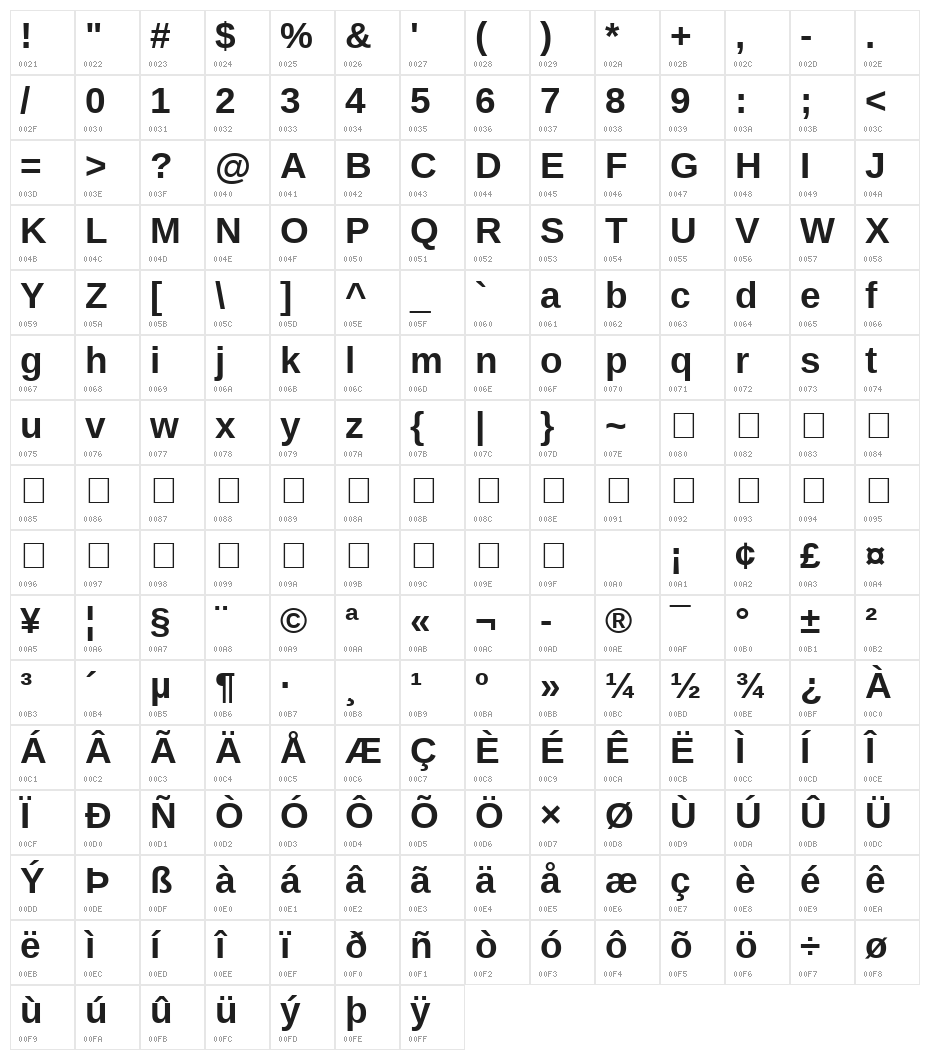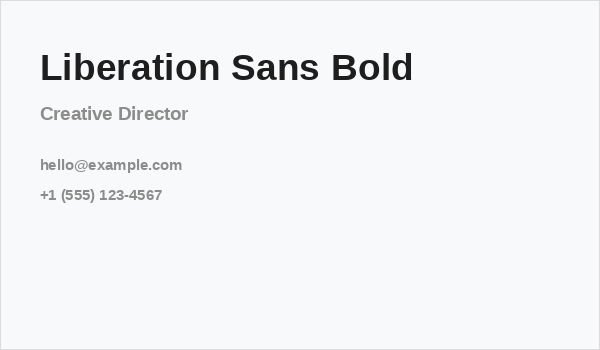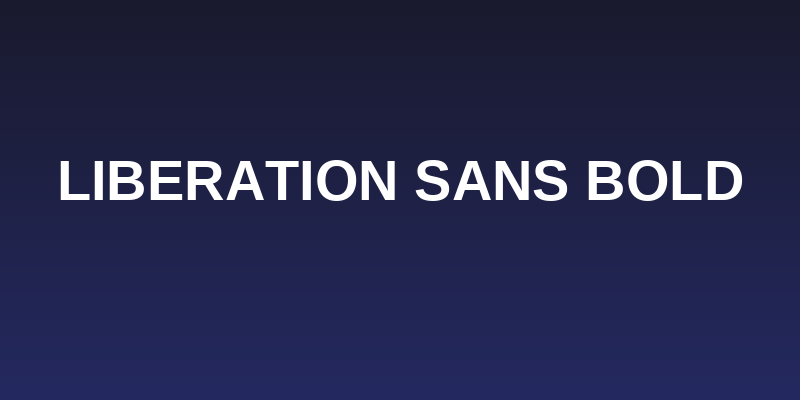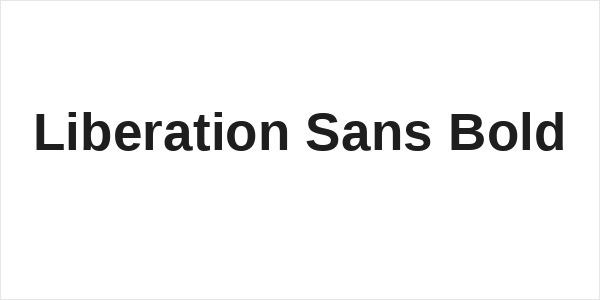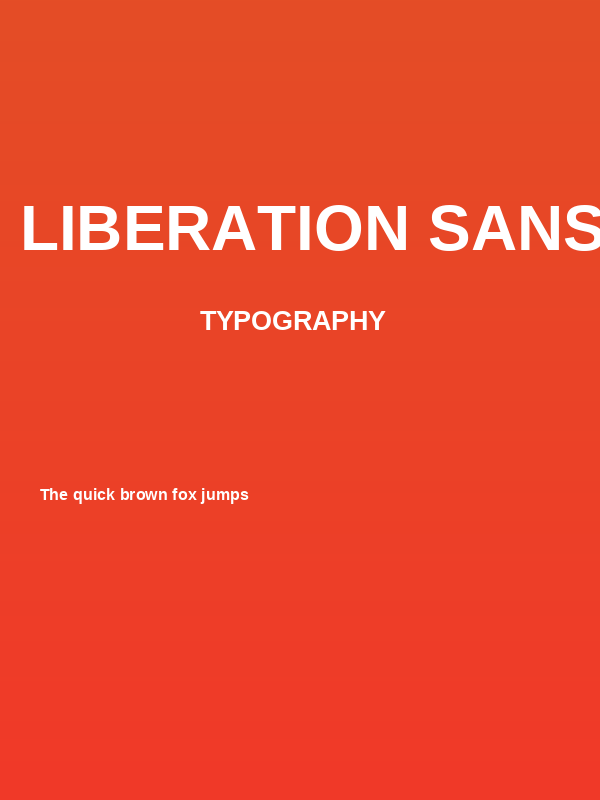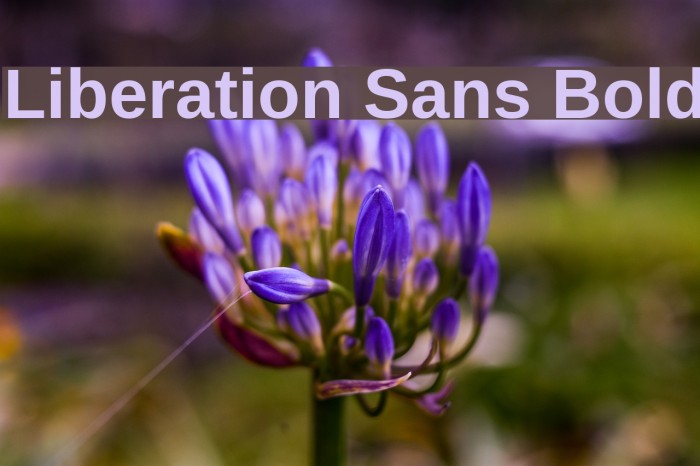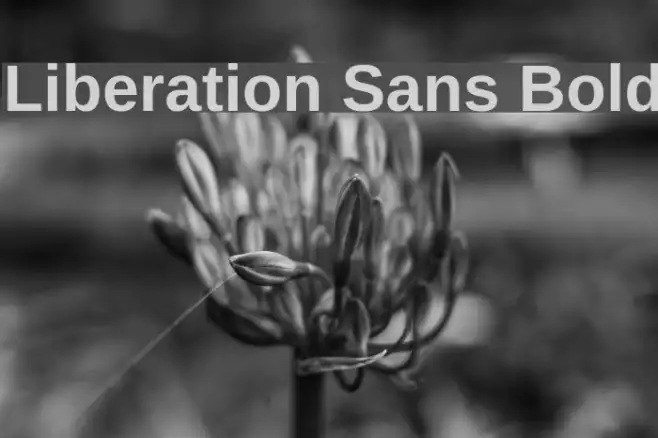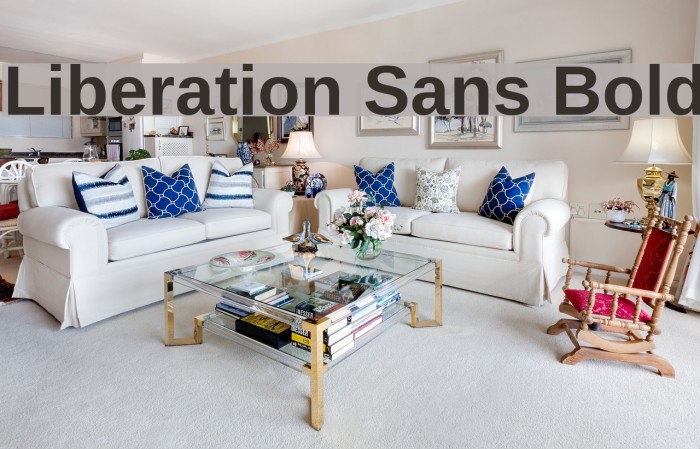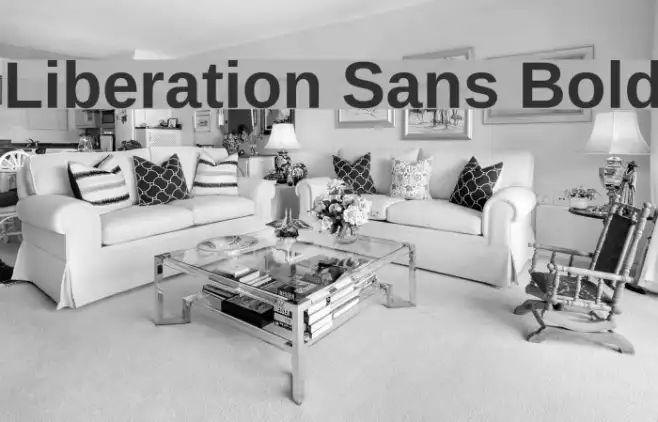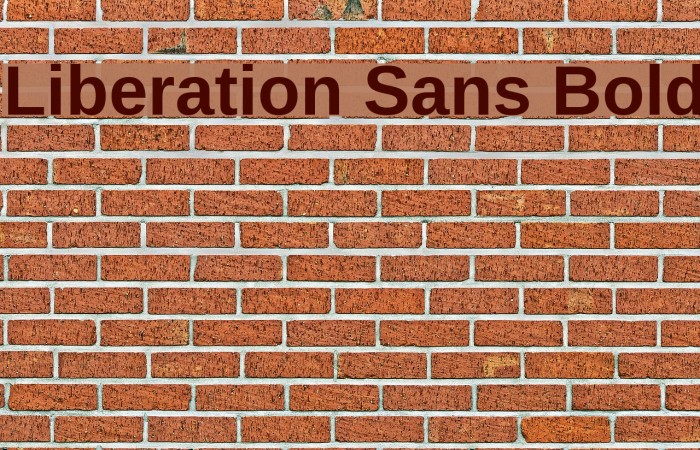
Liberation Sans Bold Font
| Cas d'utilisation | Headlines, Logos, Digital content |
| Projets proposés | Ideal for branding, advertising, headlines, and digital content where clarity and impact are essential. |